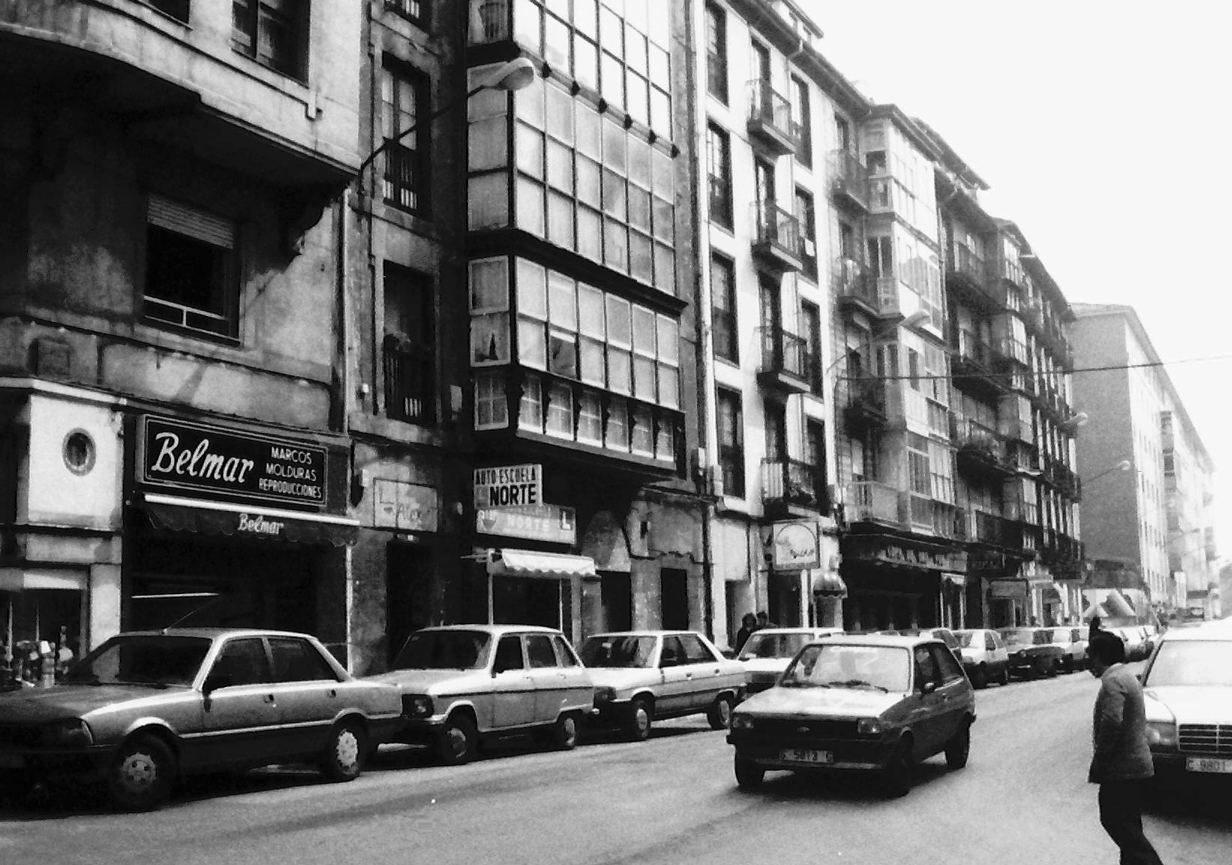
El rótulo misterioso detrás del cemento (Resuelto)
Entrada original: 21 noviembre 2015 // En la calle Guevara nº13 nos hemos encontrado con la aparición de un rótulo detrás de una capa de cemento. Es un pequeño desconchado que permite ver al menos lo que parece ser que fue una «Papelería». Lo que llama la atención es la técnica ya que es una rotulación totalmente pintada, y lo que parece una tipo «Times». Si la placa se sigue cayendo podremos ir sabiendo lo que oculta, pero de momento es un misterio. Seguiremos indagando. Si alguno tiene más info al respecto se puede poner en contacto con nosotros 🙂
Misterio Resuelto: Octubre de 2o19
Gracias a Jose Miguel Rodriguez Castillo hizo llegar a Santatipo esta foto de su archivo personal, donde nos cuenta que se trataba de la «Papelería Alex». Un papelería que el frecuentaba de pequeño para comprar comics.
La «Papelería Alex» se puede ver entre la Autoescuela Norte y Belmar. Foto: Jose Miguel Rodriguez Castillo